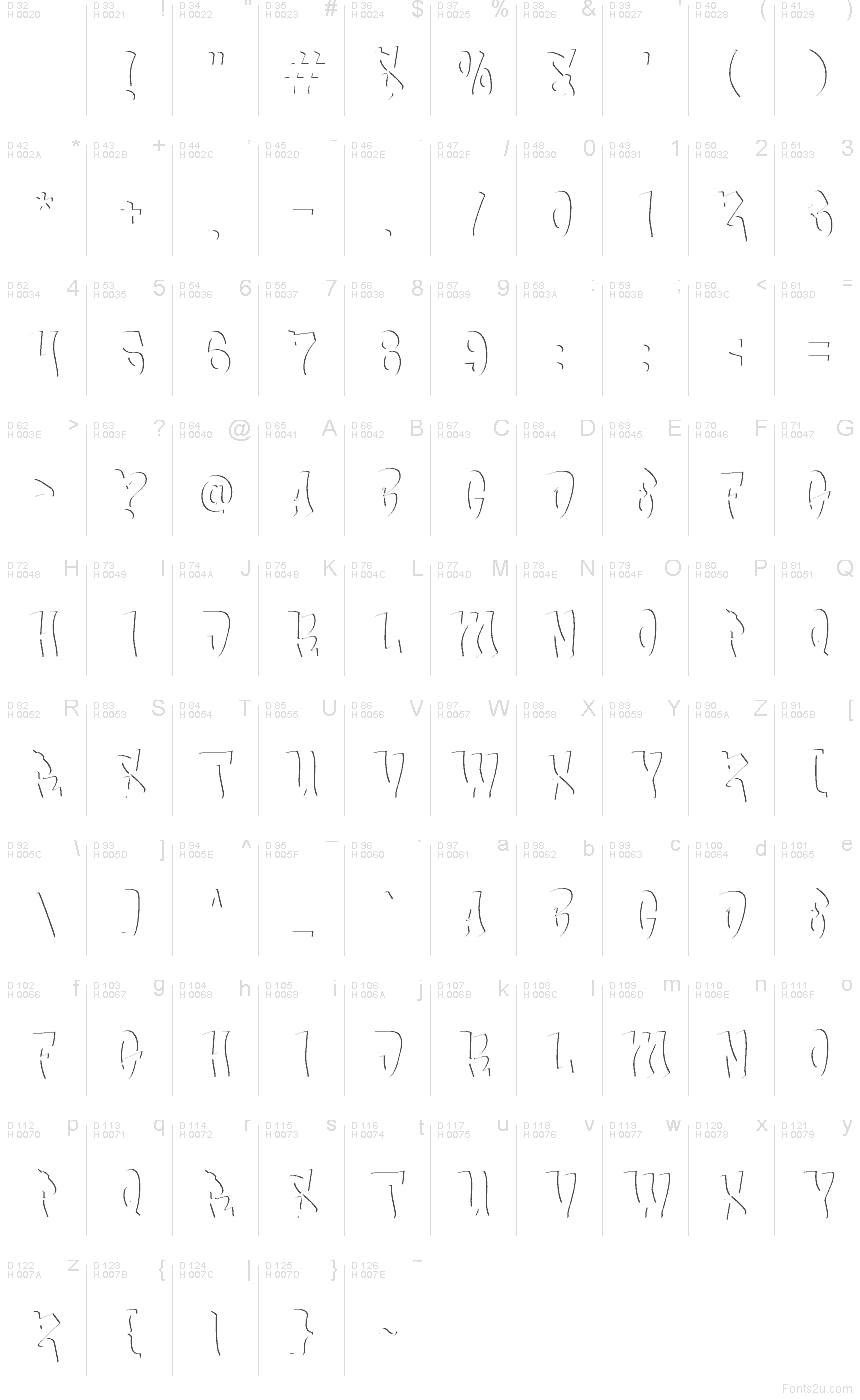
Bade Hoper inner od Cikareotype Studio je bezplatné graffiti písmo utvářené dlouhými, úsečnými tahy a volnými smyčkami, které evokují rychlé tahy fixem. Písmena působí spíše jako skica než konstruovaný design, s ostrými zlomy a zužujícími se tvary, které dodávají celé sadě neklidný rytmus.
Tento syrový pohyb skvěle vynikne na hudebních letácích, streetwearové grafice, skate plakátech, přebalech mixtapes a titulcích na sociálních sítích. Nejvíce přesvědčivé je tam, kde úzký, ručně kreslený obrys zůstane dostatečně velký na to, aby působil jako gesto, nikoliv jako dekorace – zejména u značek, které chtějí podtrhnout svůj drsný, „taggovací“ styl.